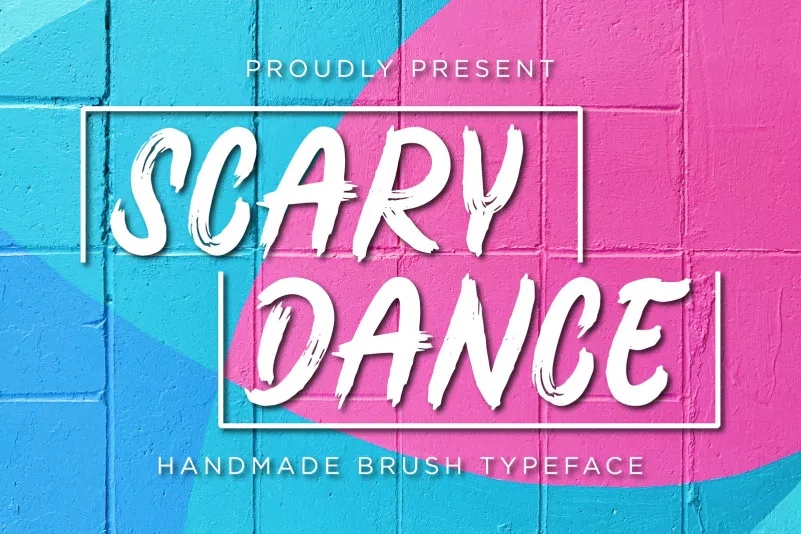
Esta é uma fonte brush que transmite leveza e destemor, ideal para qualquer atividade infantojuvenil ou projeto escolar. Seu estilo autêntico o torna perfeito para postagens publicitárias, embalagens, cabeçalhos de notícias, marcas de marca, sinalização e qualquer outro elemento urbano que você desejasse adicionar à sua peça visual. Com este tipo de fonte, transformará a mais simples das ideias criativas em verdadeiros trabalhos de arte! Seja para decorar um cartaz educacional, uma identidade de marca ou apenas enriquecer o design de suas propagandas publicitárias, a font Scary Dance certamente dará um toque de personalidade e modernidade. Se você está procurando por algo que realmente transforme os seus projetos em verdadeiros desafios artísticos, a fonte Scary Dance é definitivamente uma opção para você.